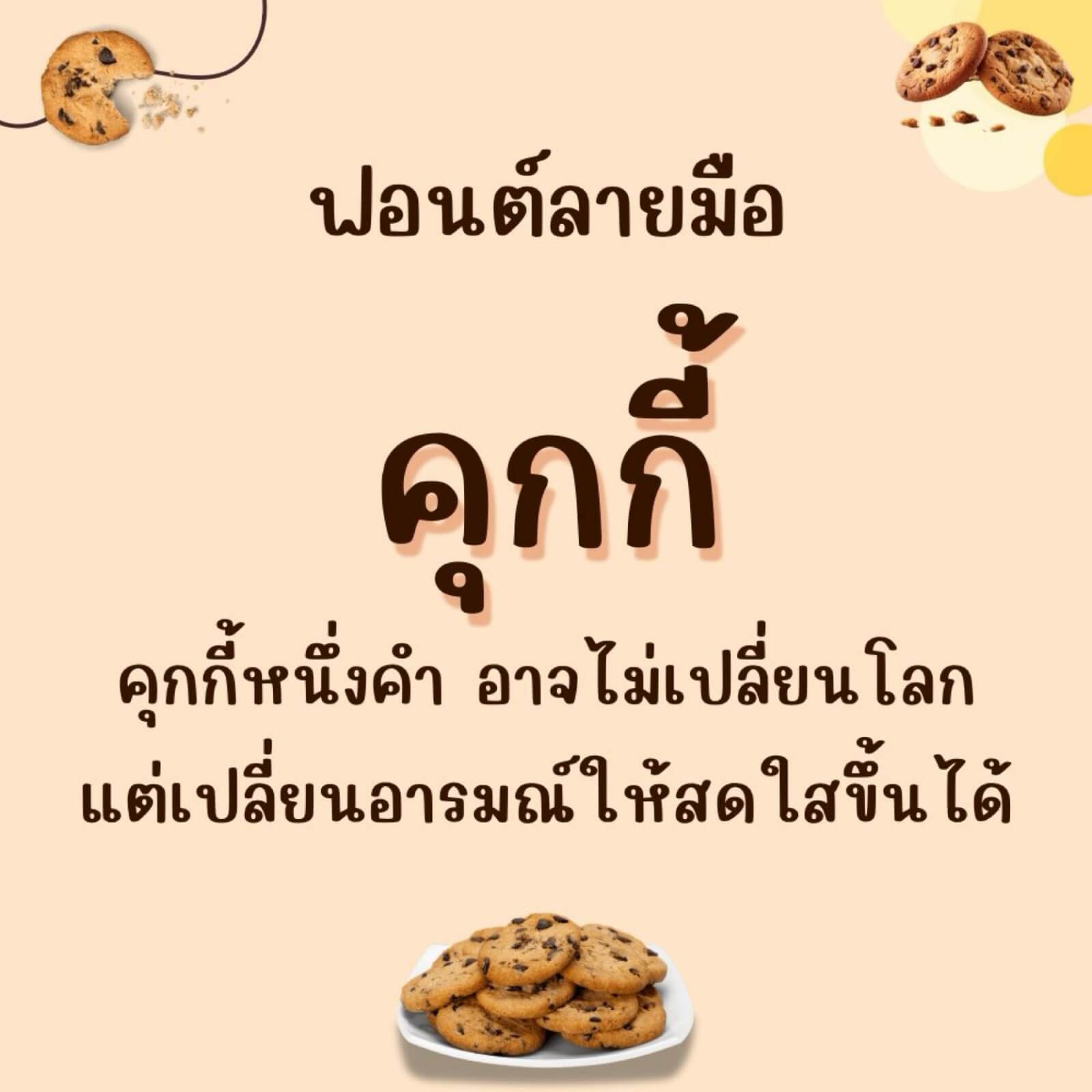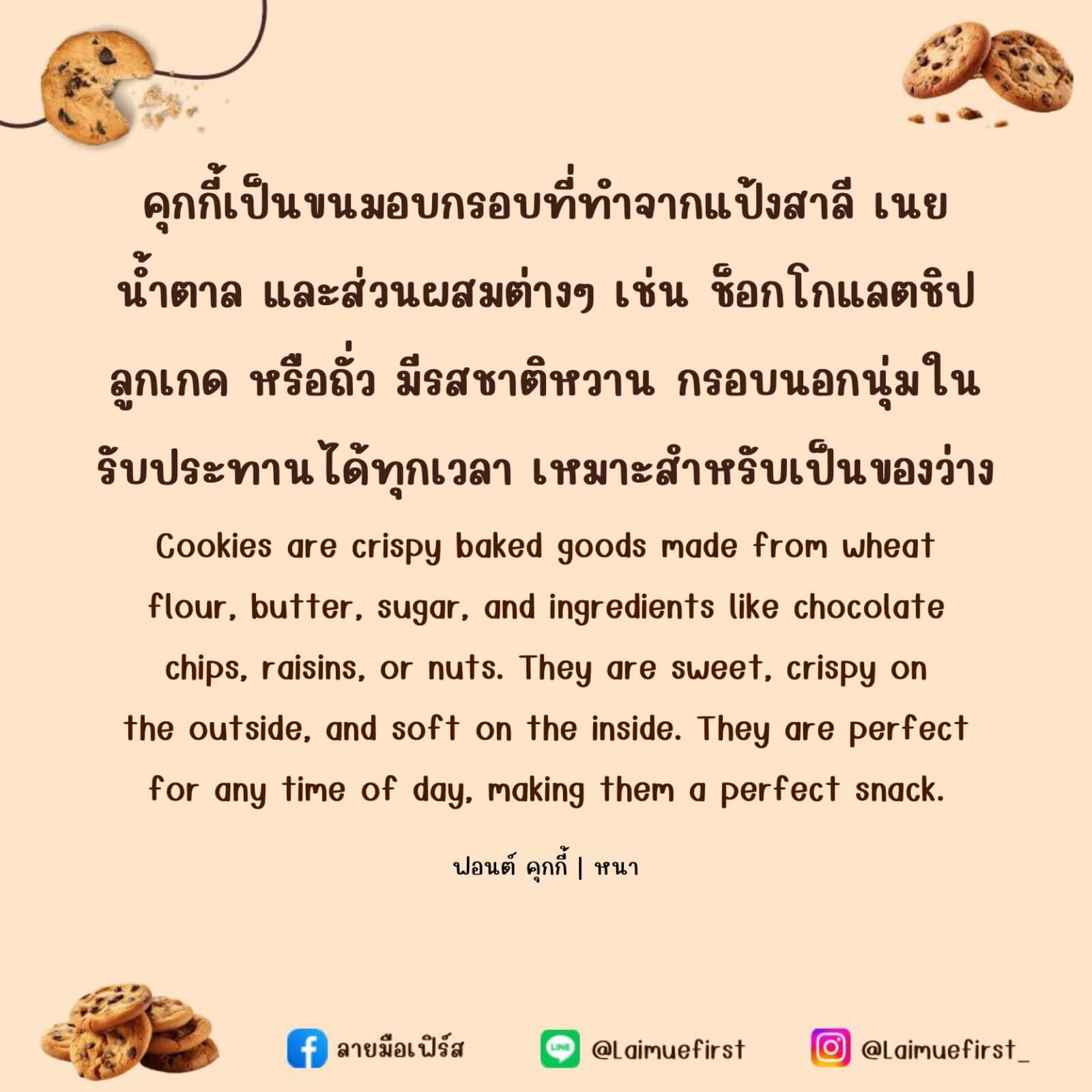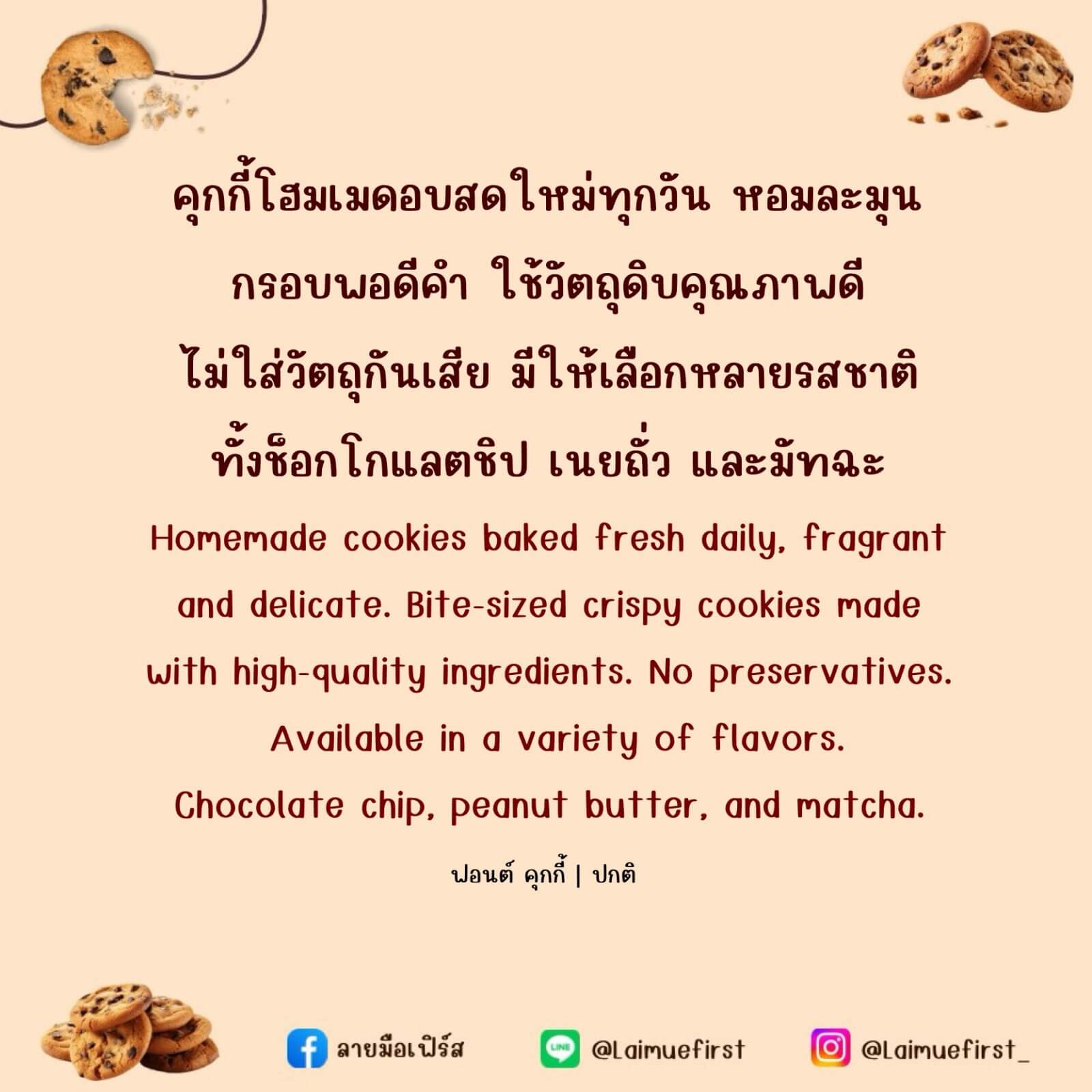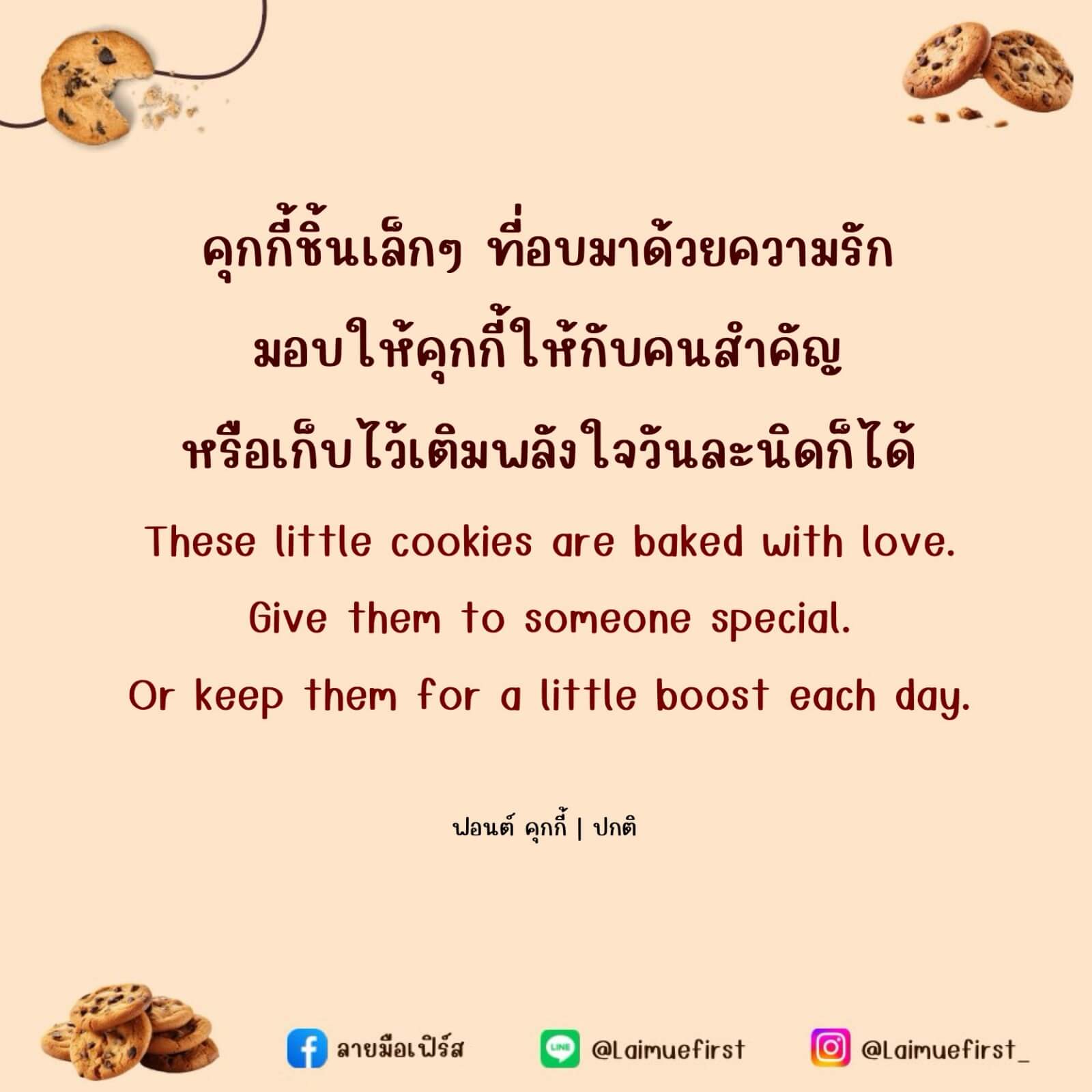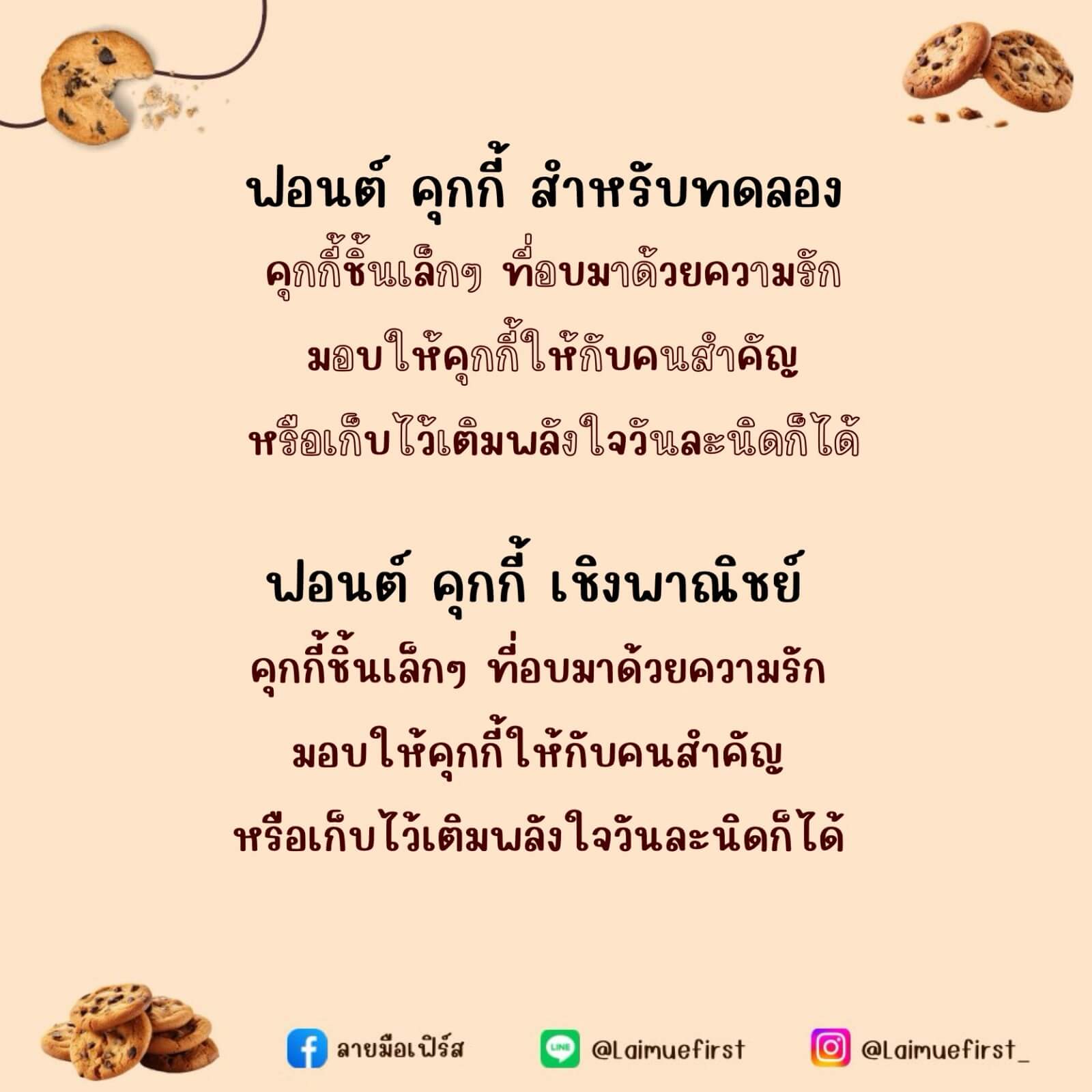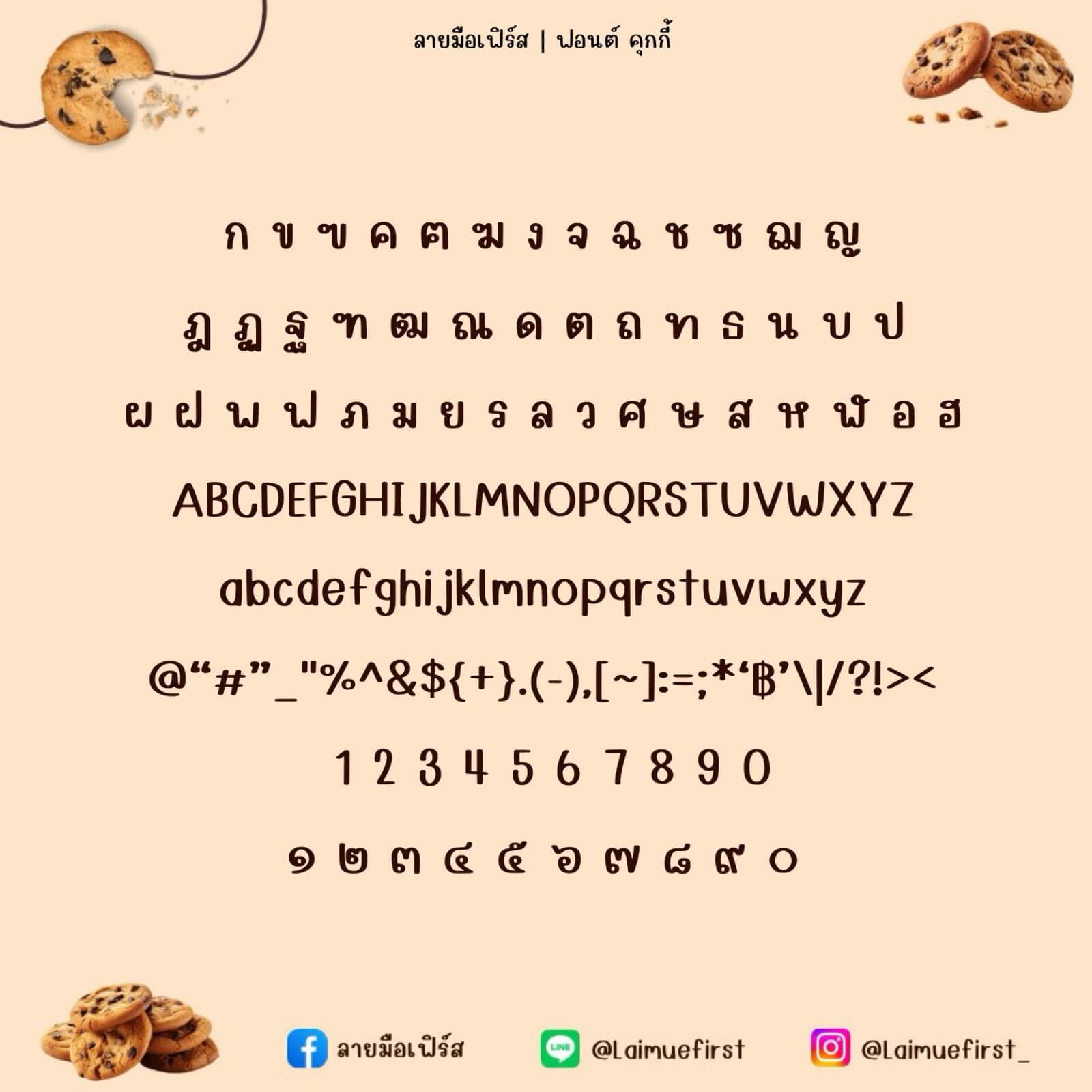
ฟอนต์ลายมือ คุกกี้ – แจกฟรีสำหรับทดลองใช้งานแบบส่วนตัว เวอร์ชันทดลอง (Demo)
- ตัวหนังสือปกติ ไม่มีตัวโปร่งปน
- ได้ฟอนต์ 3 ขนาด คือ ขนากปกติ/หนา/บาง
คุกกี้ (LMF Cookie)